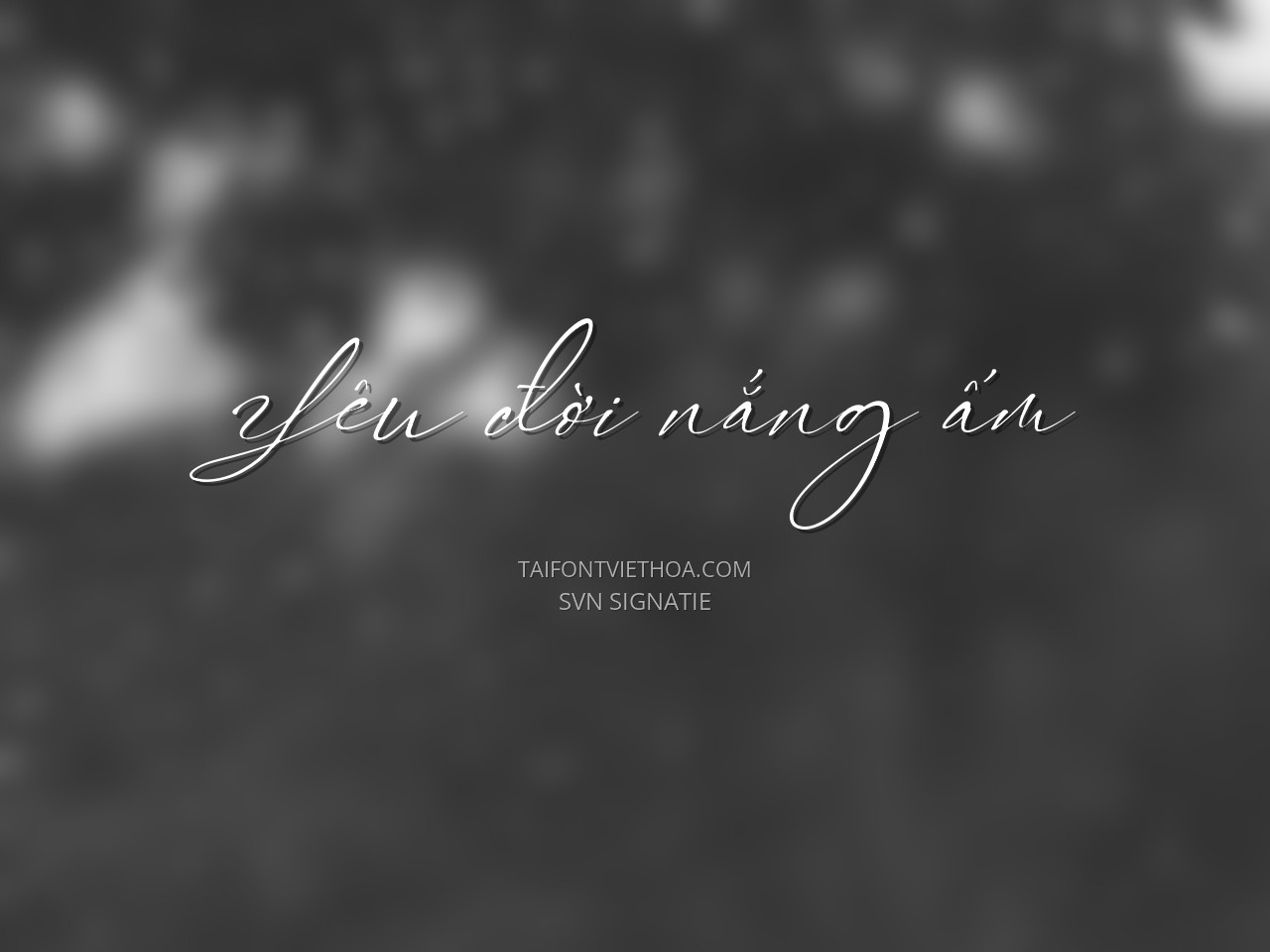
Font việt hóa SVN Signatie
Tác giả Font: Brandsemut
Giới thiệu về Signatie – Font chữ ký hiện đại, thanh lịch và cá tính
Signatie (tên gốc: Signatie Typeface) là phông chữ chữ ký (signature) hiện đại được thiết kế bởi Mozyen Studio(Indonesia) và phát hành lần đầu trên Creative Market vào năm 2019. Font gây ấn tượng với nét bút máy tự nhiên, các đường cong mềm mại, độ nghiêng vừa phải và sự kết hợp giữa thanh mảnh và dày dặn ở từng ký tự. Bản quốc tế của Signatie hỗ trợ trên 60 ngôn ngữ Latin, tích hợp alternates, ligatures và ký tự đặc biệt giúp cá nhân hóa thiết kế linh hoạt trên mọi nền tảng số và in ấn.
Bản SVN Signatieđã được STYLEno.1 FontsViệt hóa trọn bộ, bổ sung dấu tiếng Việt, cân chỉnh kerning và tối ưu hóa hinting để font hiển thị sắc nét ở mọi kích thước chữ. Đội ngũ taifontviethoa.comđã trực tiếp kiểm thử thực tế trên Photoshop, Illustrator, Canva…, đảm bảo không lỗi dấu, không vỡ nét dù dùng làm tiêu đề lớn hoặc nội dung nhỏ. Signatie Việt hóa là lựa chọn tối ưu cho các dự án cần font chữ ký hiện đại, phù hợp cho branding cá nhân, thiệp mời hoặc các thiết kế cao cấp.
Đặc điểm thiết kế, ứng dụng và ngành nghề phù hợp
Signatie thuộc nhóm chữ ký (signature script), nổi bật với các nét chữ thanh thoát, bo tròn nhẹ, nhịp điệu tự nhiên, tạo cảm giác thân thiện và chuyên nghiệp. Bộ alternates, ligatures đa dạng giúp dễ dàng cá nhân hóa tiêu đề, logo, thiệp mời hoặc các sản phẩm handmade cao cấp. Signatie phát huy tối đa hiệu quả khi dùng cho branding cá nhân, chữ ký số, hồ sơ doanh nhân, sản phẩm handmade, thiệp mời hoặc nhãn hàng thời trang cao cấp.
Ứng dụng tiêu biểu
– Logo & nhận diện:Thương hiệu cá nhân, agency sáng tạo, shop handmade, beauty salon.
– Ấn phẩm truyền thông:Chữ ký số, profile doanh nhân, story social media, thiệp mời sự kiện.
– Bao bì & nhãn mác:Nhãn sản phẩm cao cấp, bao bì handmade, sổ tay, thiệp cảm ơn.
Ngành nghề phù hợp